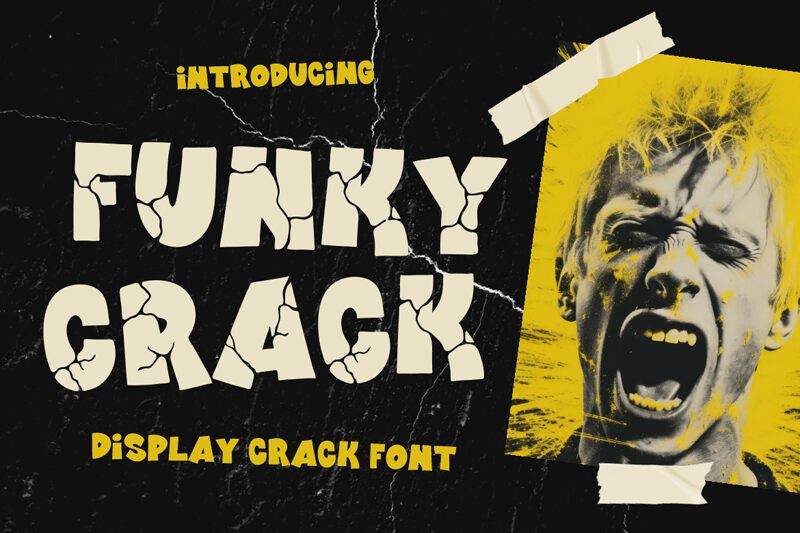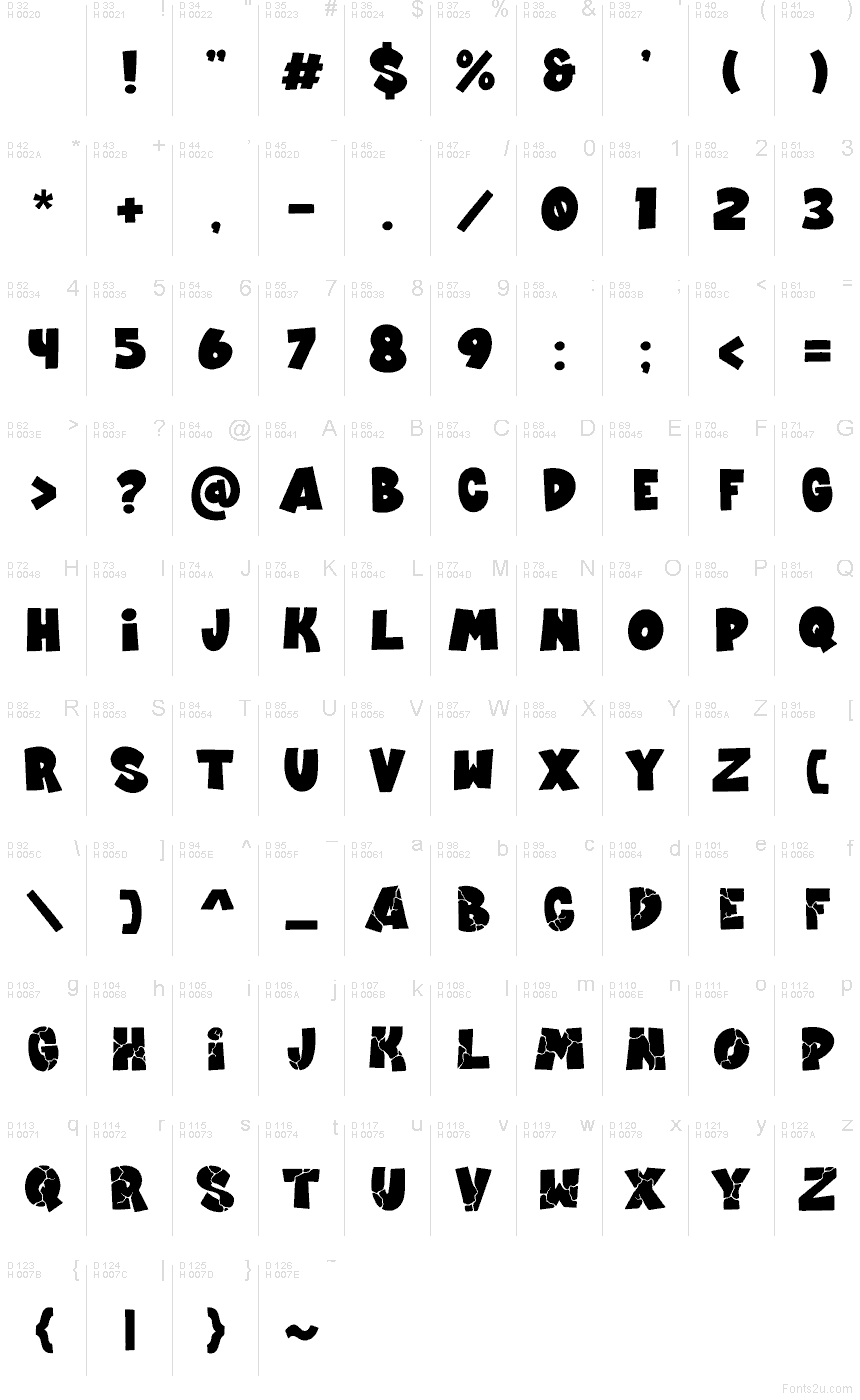
Funky Crack di Shanaf Studio è un font cartoon gratuito per titoli, caratterizzato da lettere grandi e massicce divise da crepe profonde, come se fossero state scolpite nella pietra spezzata. Le forme sono pesanti e semplici, ma quelle fratture irregolari conferiscono al carattere un impatto giocoso, più vicino allo stile fumetto che a quello grezzo.
È l'ideale per titoli di poster, loghi di giochi, volantini, packaging per bambini e miniature di YouTube dove serve un font gratuito con un tocco d'effetto integrato direttamente nelle lettere. Dato che l'effetto crepa si ripete su tutto il font invece di limitarsi a un singolo carattere, funziona benissimo anche per titoli, schermate di avvio e grandi monogrammi che richiedono un impatto visivo in stile cartoon immediato.